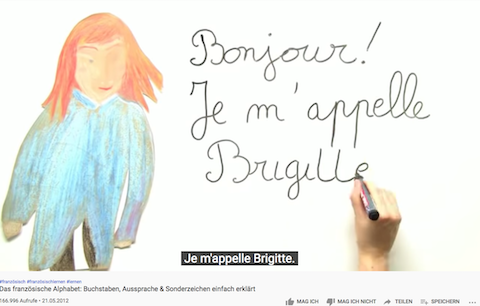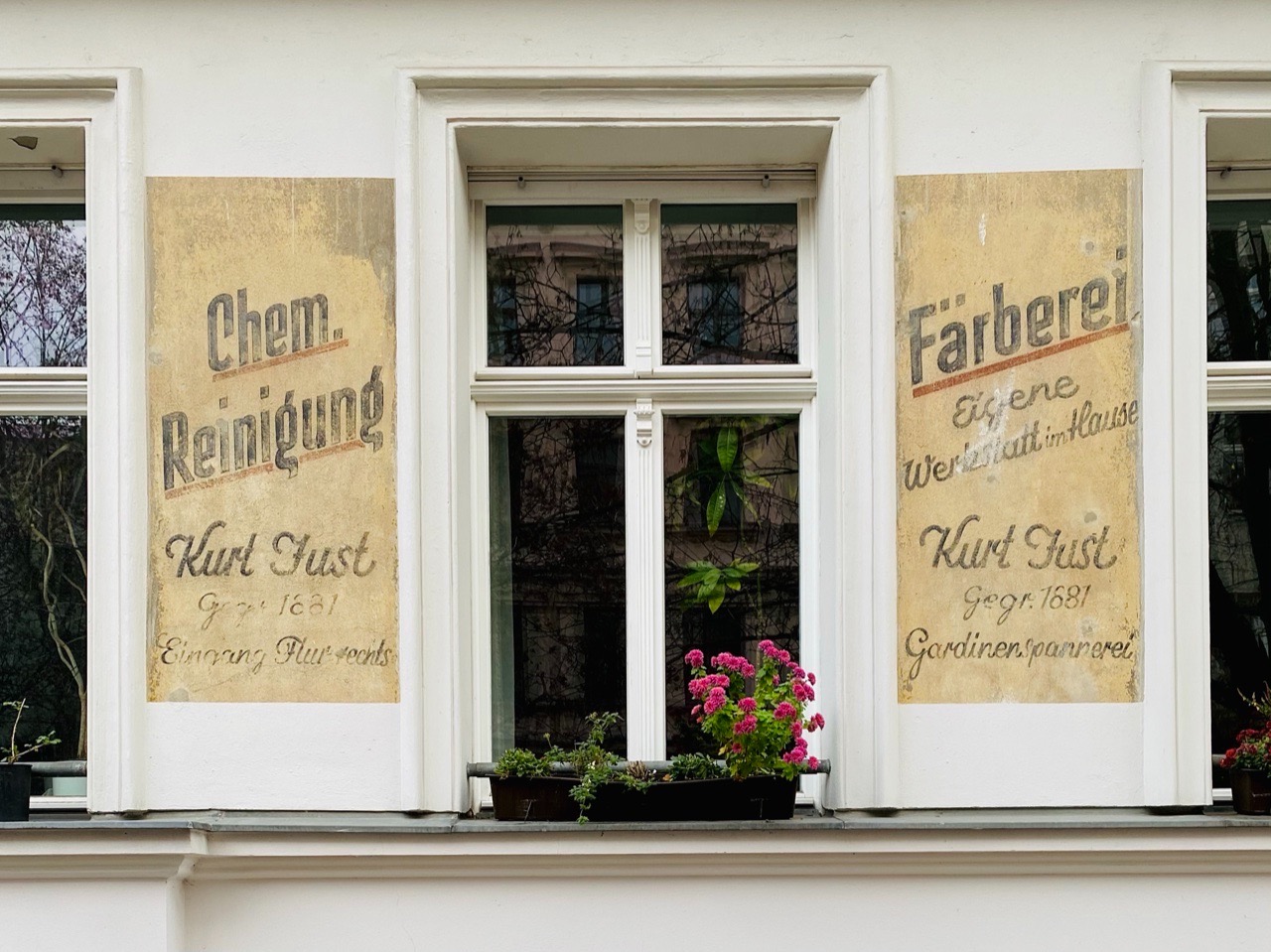
Dieses r ist im englischen üblich.
Ja, aber nicht im mir bekannten Kontinental-Europa (soweit mir da Schriftstücke entegegen kamen). Laut Onkel Wiki wurde der Bürgereid aber ab 1845 auch auf Englisch oder Französisch abgenommen, vielleicht deswegen die internationaleren Formen in der Kalligraphie?
Unschön und unnötig, da hier ja kein Randausgleich für Blocksatz erfolgen muss, ist allerdings die Silbentrennung in der erstenZeile (»be-wahrten«).
Das kleine r mit Schlaufe ist inzwischen zwar aus der Mode* gekommen, war/ist aber in »Kontinentaleuropa« recht verbreitet. Siehe z. B. hier. Im Französischen ist es sogar eher der Standard.
*) Durchs Hobby-Handlettering kommt es gerade wieder in Mode.
Und wenn Du das jetzt für sehr chauvinitisch hälst: Ja, das ist es. Es gibt in Hamburg übrigens auch innerhalb der Stadt eine gewisse Hierarchie, die durch den Wohnort definiert wird: Du kannst beispielsweise auf der falschen Seite der Alster wohnen. Oder schlimmer noch auf der falschen Seite der Elbe. Wie so oft, kannst Du aber durch Zeit (also besser Deine Enkel) und Geld (Wohnort wechseln) Deinen Status in der (eingebildeten) hamburger Bevölkerung ändern.
Gewisse Familien
Lustigerweise genau die Familien, die Namensgeber von Straßen sind, im Umgang oft überhaupt nicht. Die jedoch kennenzulernen ist etwas herausfordernd -- man bleibt halt unter sich. Am schlimmsten empfinde ich die Neureichen.
Nicht umsonst gilt Hamburg als ausgesprochen britische Stadt.
Habe mir gestern Baumkuchen aus Cottbus bestellt. Mal sehen ob der typografisch mithalten kann! :-)
Falscher Strang aber cool.
Ich hatte kurz darüber nachgedacht aber fand die Anwendung mit den »Schnörkeln« dann doch zu nett und zu wenig Stiefel ... 🤓
Ich mag »C« und »g« von »Chem. Reinigung« … das »H« bei »Hause« ist aber auch nicht zu verachten.
Diese c und g form kommt ja bei mir in 2 Schriften vor, Diese Buchstabenformen aren in der Entstehungszeit der Wandanschrift im Deutschsprachigen Raum recht verbreitet.
Allerdings findet sich das c mitder rechts heruntergezogenen Linie  dort nur bei den Kleinbuchstaben, weil sich das schablonierte c dann  leicht zum e ergänzen lässt